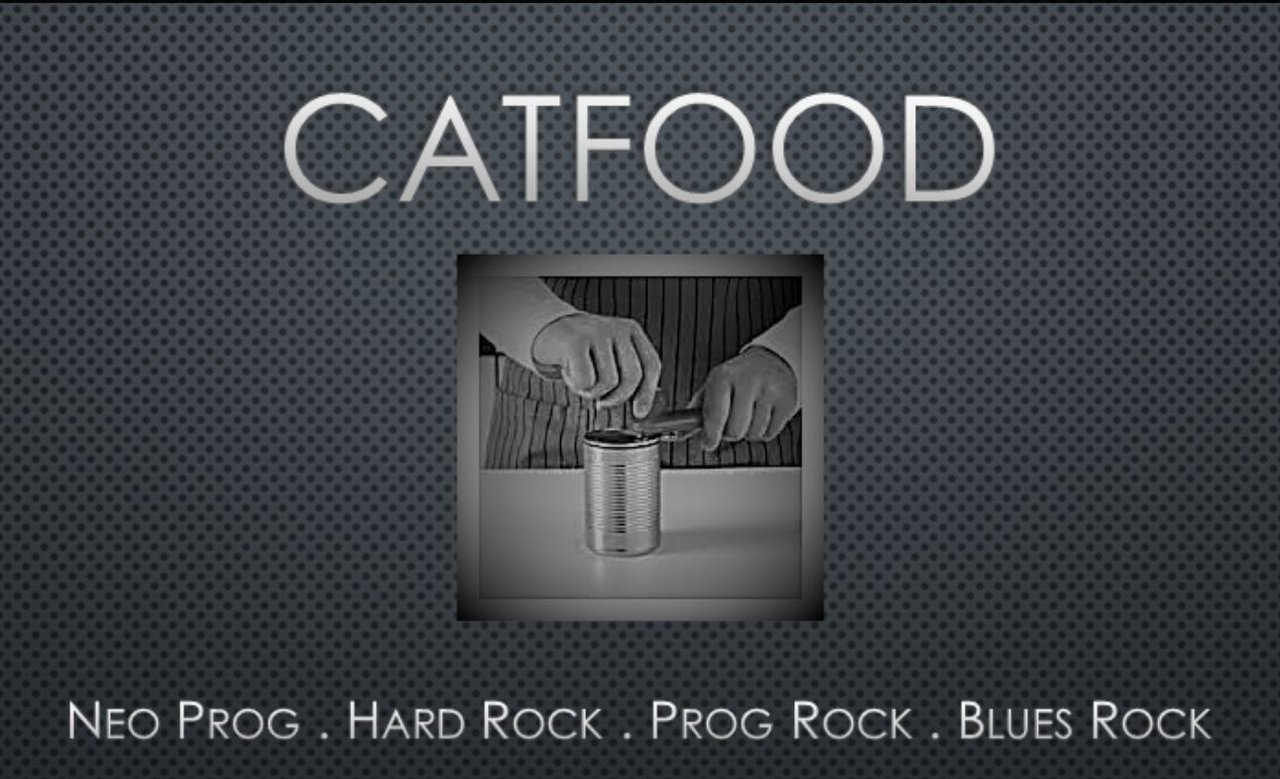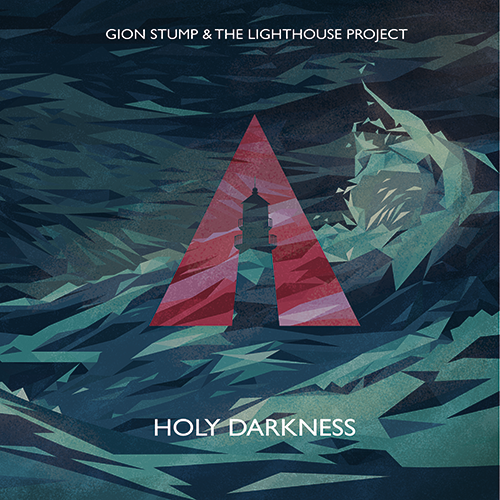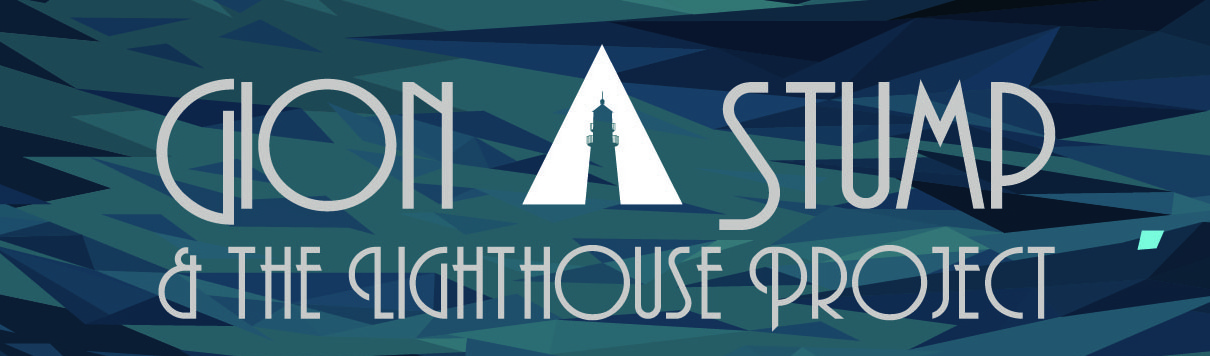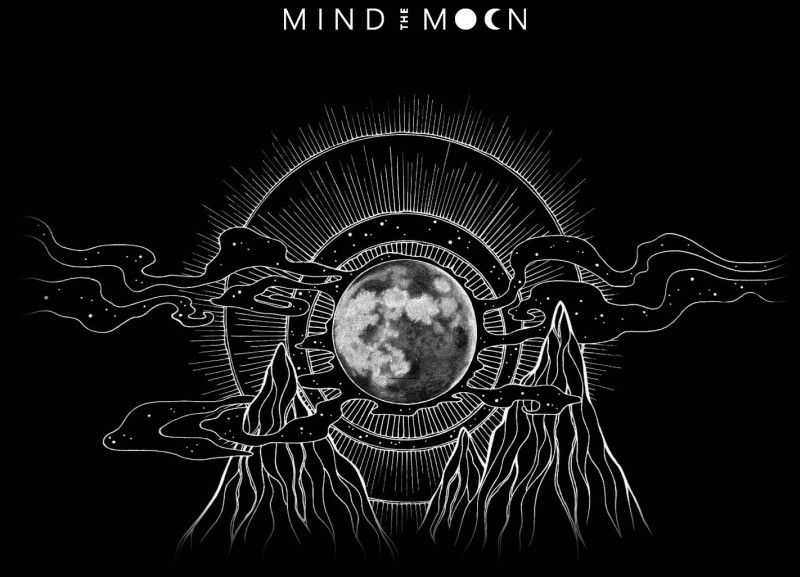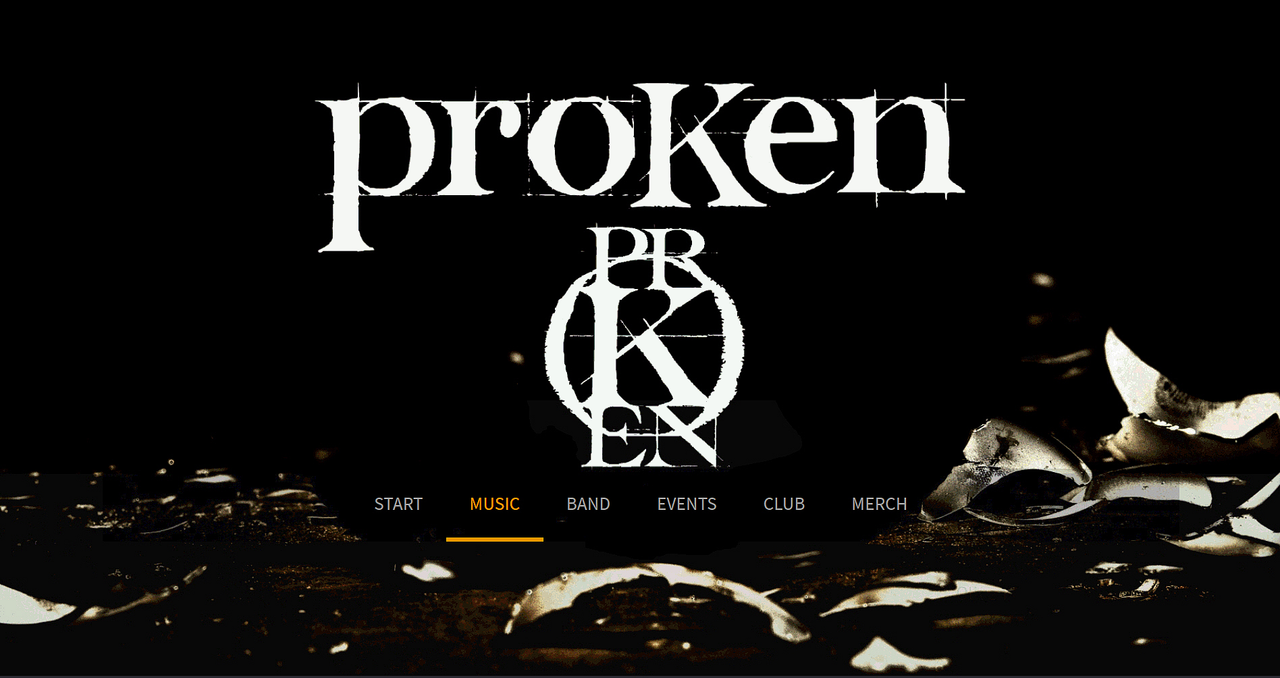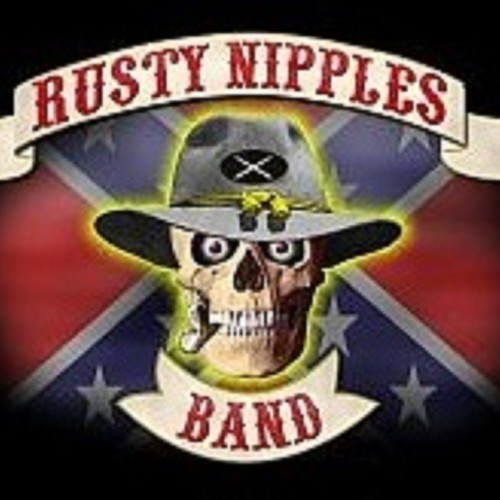
Euer Bandlogo-Artwork-Schriftart... her damit...!
Ok, und jetzt zu meiner damaligen Truppe. Hab da getrommelt.
Erster Name war „Bay 13“, deutsch etwa „Lagerhalle 13“; das war der damalige Probenraum. Eine Halle. Mit Heizungen. :D
Danach hießen wir „the decibels“. Peinlich. Aber laut! Muss Logo suchen.
... und danach hatten wir noch nen dritten Namen, aber ich bin zu feige, um den zu nennen. :II
Sehr geil, dass dieser Fred jetzt Fahrt aufnimmt und richtig interessant ist! Ich werde morgen unsre Story dazu posten.
Wir hatten zuerst das orange Logo. Wir haben da eigentlich wenig Einfluss darauf genommen und unserer Designerin relativ freie Hand gelassen.
Dann wollten wir ein Backdrop und haben dazu wiederum von ihr ein Design erstellen lassen, welches dann einen neuen Schriftzug beinhaltete, den wir dann auch für sämtliche anderen Belange übernommen haben.
Der neue Schriftzug ist aber auch bereits mal überarbeitet worden, der Leuchtturm hatte zuvor eine leicht andere Form und wurde dann im Zuge des neuen Albums, Backdrop etc. nochmals überarbeitet. Der Leuchtturm und die Wellen finden sich so dann auch auf dem Albumcover wieder:
... ja, genau, tät somit aber ganz doll zum Foto passen; zum Park und so... Oder wie wärs mit „Kings of Etepetete“? :D Bin sehr gemein, ich weiss; ich stolperte einfach über das höchst edle Teil, auf welchem das Aronal Marine Pearl-folierte Gretsch, äh, schwebt. ....
Haha, das ist das Gegenteil von "edel" (nur auf dem s/w-Foto nicht gut erkennbar) - nämlich eine alter Kinderteppich von Rudis Sohn (das Teil muss aus den mittleren 1960er Jahren stammen) mit Straßen usw. drauf :D... guckst Du:
Die Richtung ist klar (leider schlechte Bildqualität in dieser Datei), das Logo vor Äonen in Photoshop gebastelt:
... und danach hatten wir noch nen dritten Namen, aber ich bin zu feige, um den zu nennen. :II
Sooo schlimm wird's schon nicht gewesen sein ;-)... meine erste Band hieß so, wie der Song hier im Video (auch wenn unsere Musik mangels Instrumentenbeherrschung bei weitem nicht so cool klang wie die Headboys :II- und meine Kollegen das Lied auch gar nicht kannten :D) ...
Unser Namensfindungsprozess zog sich endlose 9 Monate hin. Progressive Rock mit klassischen Passagen und hartem Rock, krummen Taktarten und unerwarteten Chordwechseln - im Namen und visuell abzubilden - nicht ganz einfach, zumal wir sehr 6 sehr unterschiedliche Persönlichkeiten in der Band sind.
Der Name sollte auffallend, lieber etwas sperrig als zu glatt sein (wie die Musik), etwas dunkel und geheimnisvoll aber nicht unbedingt aus dem Metal- oder Hardrock-Genre, sondern auch die klassische Seite (Vivaldi, Bach ... ) transportierend. Und dann am besten im Internet recht schnell findbar, also eher einzigartig und auch einprägsam.
Über Excel-Tabellen mit Punktebewertung bis zu vielen spontanen Ideen, nichts war konsensfähig oder - natürlich - durch andre Bands schon belegt. Bei einer gemeinsamen Feier sollte dann unter allen Umständen eine Entscheidung fallen. Am Ende blieben "Inprognito" und "proKen" übrig, auch hier gingen die Meinungen erwartungsgemäß auseinander. Dann liessen wir die Mädelz am Tisch entscheiden und es war eindeutig - es sollte "proKen" sein: ein phonetischer Kunstname aus "Progressive" + "Broken" + "Token"...
Bei der Frage nach dem Design wurde es schwierig, auch in der Gestaltung sollte sich die muskalische Aussage wiederfinden, und gute Lesbarkeit war wichtig vorausgesetzt. Unser Chef-Layouter, Gestalter, Verleger und Profi für Design und Logo wollte absolut nicht tätig werden wollte, weil der den gleichen schwierigen Diskussionsprozess fürchtete. Am Ende fiel die Wahl auf mich (OMG!!), und ums kurz zu machen, das Ergebnis sieht jetzt so aus (erster Entwurf, Internet Präsenz, Facebook etc. entstehen gerade):
@SonicDomination sehr geiles Album Cover :great:
:-) - meinte unser Keyboarder auch...
Der Name ist ein Titel von King Crimson, das Design 10 Min. Powerpoint :D
Hat die Freundin unseres Sängers "gebastelt":
[...] die Headboys [...]
Geiiil! Jeder einzelne von denen! Der Drummer - mit dem Poloshirt mit aufgestelltem Kragen! Der Gitarrist mit seinen zackigen Zuckungen! Der Tastenvirtuose mit seiner Gestik! Gahaiiil! Von nun an werde ich mir immer, wenn ich depressiv bin, dieses Video anschaun! :D Merci! :-) PS: Nee, den dritten Namen verrate ich nicht. Zu peinlich. Zu feige.
Damals für meine Ex Band gebastelt: